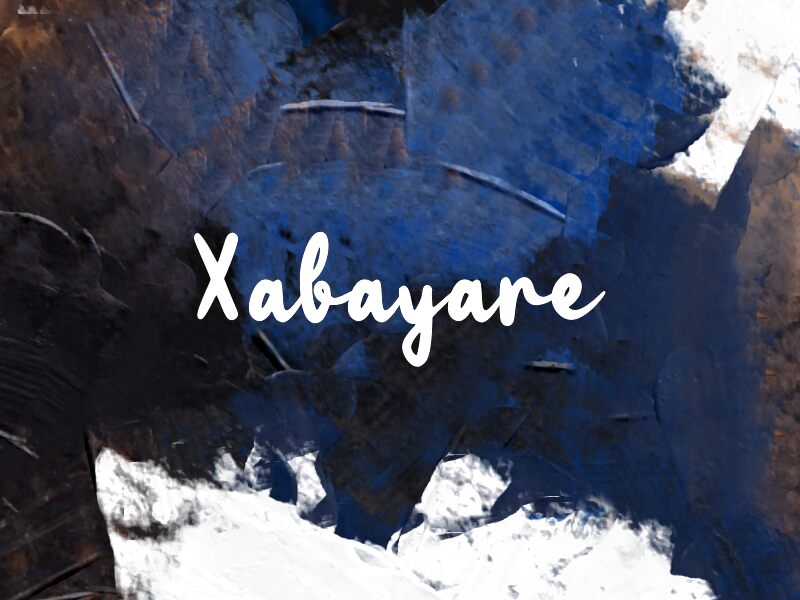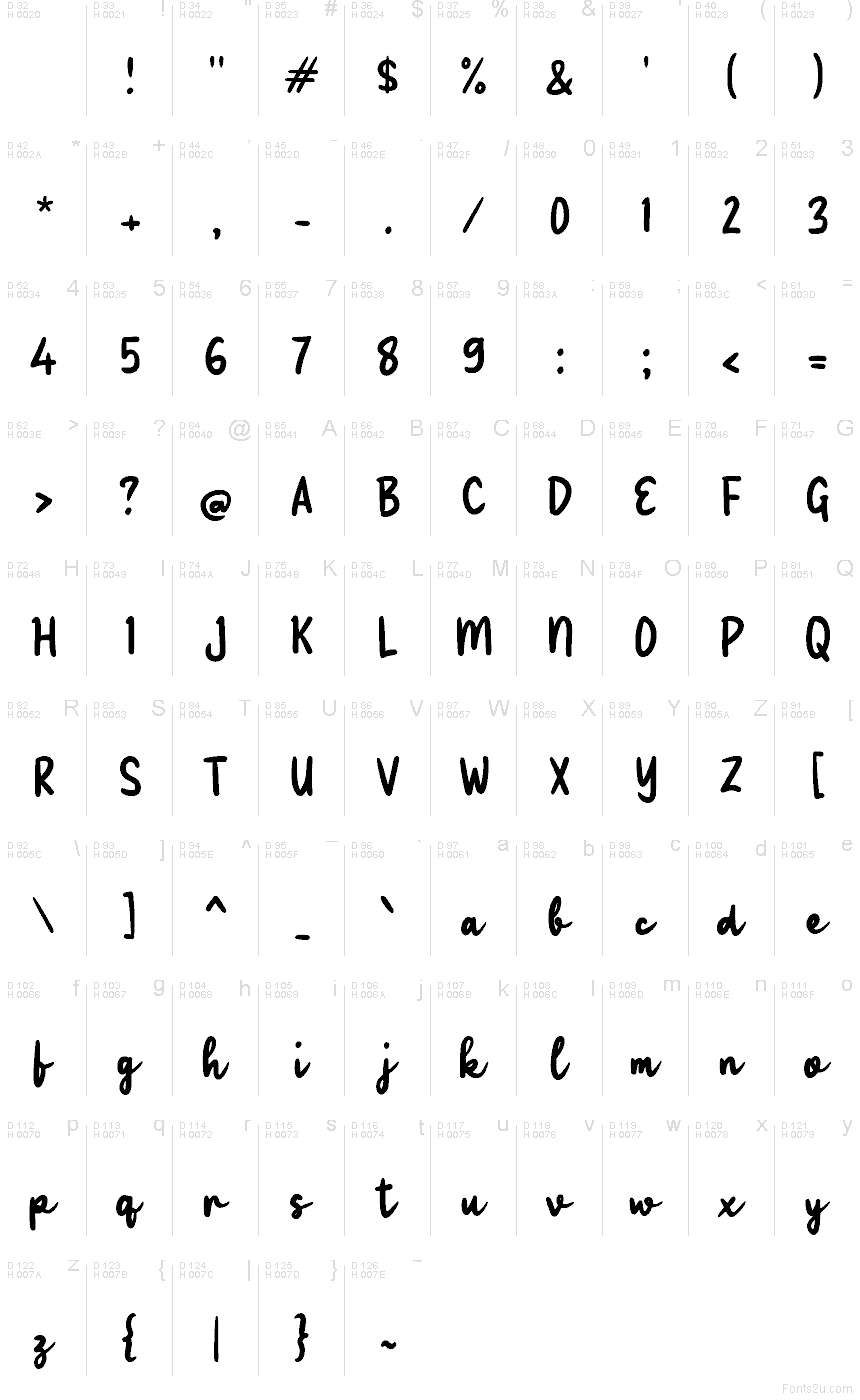
Xabayare
Xabayare di Wep è un font gratuito in stile brush script, caratterizzato da un tratto casual e moderno. Le lettere scorrono con un ritmo scuro e inchiostrato, alternando tratti spessi, giunture arrotondate e una lunga discendente che conferisce al font un'aria spontanea, quasi fosse una nota scritta a mano, piuttosto che una calligrafia ricercata.
È perfetto per citazioni sui social, branding di locali, packaging, titoli di poster e logotipi brevi dove quel movimento fluido fa la differenza. Essendo un font gratuito, Xabayare è ideale anche per titoli e copertine, specialmente quando si vuole che una parola o una frase breve appaia immediata, personale e leggermente audace.